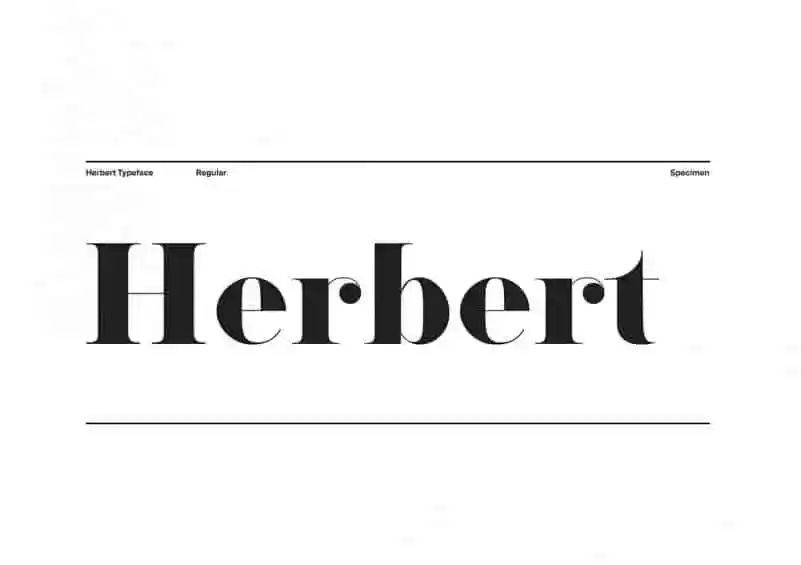
Herbert Serif é uma nova adição à família de fonts serif, lançada pela 99designs em 2019. Desenvolvida pelo estúdio de comunicação K95 por Danilo De Marco, Herbert apresenta um estilo único e elegante que adicionará profundidade a qualquer projeto. Esta fonte do tipo didone é especialmente adequada para uso tanto em impressão quanto em produtos digitais. Suas linhas retas e traços robustos não apenas fornecem uma aparência forte e poderosa, mas também garantem leitura confortável mesmo em grandes tamanhos de texto. Ideal para headlines ou qualquer outra seção do design gráfico que deseja dar um toque atraente e moderno. Herbert é perfeito para designers buscando adicionar uma personalidade única a seus trabalhos.